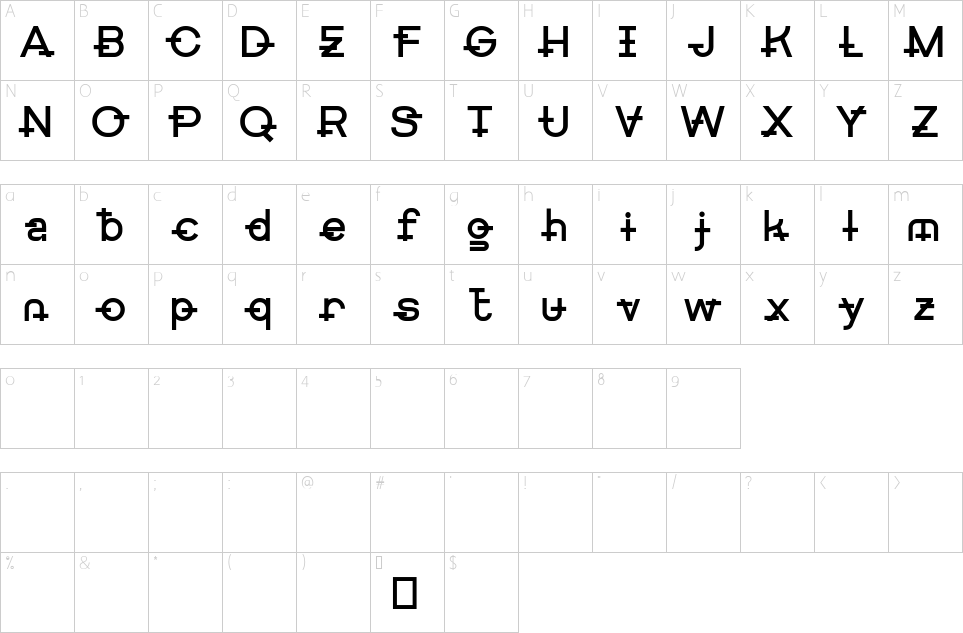
A fonte Getboreg Minus Tech é uma excelente escolha para designers gráficos que buscam um estilo minimalista e tecnológico. Desenhada por ffeeaarr, esta fonte foi criada com precisão e simplicidade, ideal para projetos digitais modernos. Com o formato de uso suportando tanto Windows quanto Mac, é uma escolha versátil para criar designs que se adequam a qualquer plataforma digital. Seja em aplicativos de mensagens ou páginas web, Getboreg Minus Tech oferece um visual atraente e profissional, perfeitamente adaptado ao universo da tecnologia contemporânea. A fonte foi baixada 912 vezes pela comunidade de designers, o que demonstra sua relevância no mercado. Se você está buscando uma opção sem custos para adicionar um toque único a seus projetos digitais, Getboreg Minus Tech é definitivamente algo a considerar.